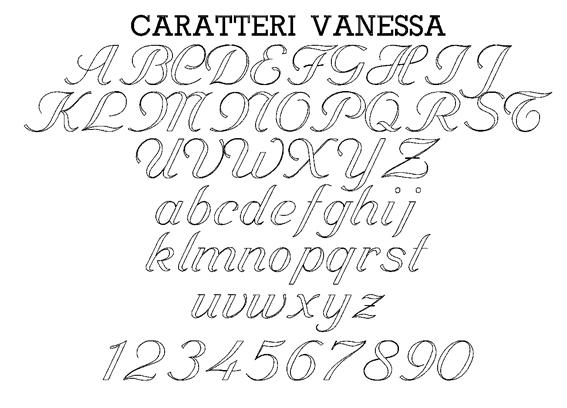
Gravurschrift VANESSA 56 5L als Satzschrift gesucht
Auf vielen Seiten gesucht und doch nicht gefunden …
Gibt es die Gravurschrift „Vanessa 56 5L“ – eventuell unter anderem Namen – auch als Satzschrift (PS, OT, TT …) für Mac? Das einzige Kaufangebot (http://fonts.gravostore.com/product.php?id_product=226) ist mit einem dickem Ausrufezeichen „Only for users of GravoStyle Software …“ versehen und so vermutlich nicht für Illustrator & Co geeignet.
Kann jemand helfen?
Deine gezeigte ist die 2L, nicht die 5L. Bei der 2L werden nur die Umrisse graviert.
ich suche diese Schriftart Vanessa 56 2l für den PC (Illustrator). Gibt es die Irgendwo zukaufen?